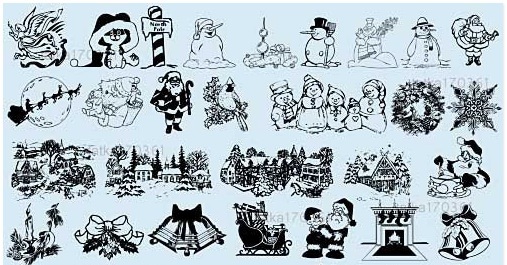
40款卡通圣誕節(jié)字體是用各種圣誕節(jié)道具制作而成的,是一款極具圣誕氣息的字體。圣誕節(jié)馬上就來(lái)來(lái)咯,卡通圣誕節(jié)字體送給大家。每年的12月25日是圣誕節(jié)(Christmas),基督徒慶祝耶穌基督誕生的節(jié)日。圣誕節(jié)是很多西方國(guó)家的公共假日,這天全家人會(huì)圍坐在圣誕樹(shù)下共進(jìn)美餐。